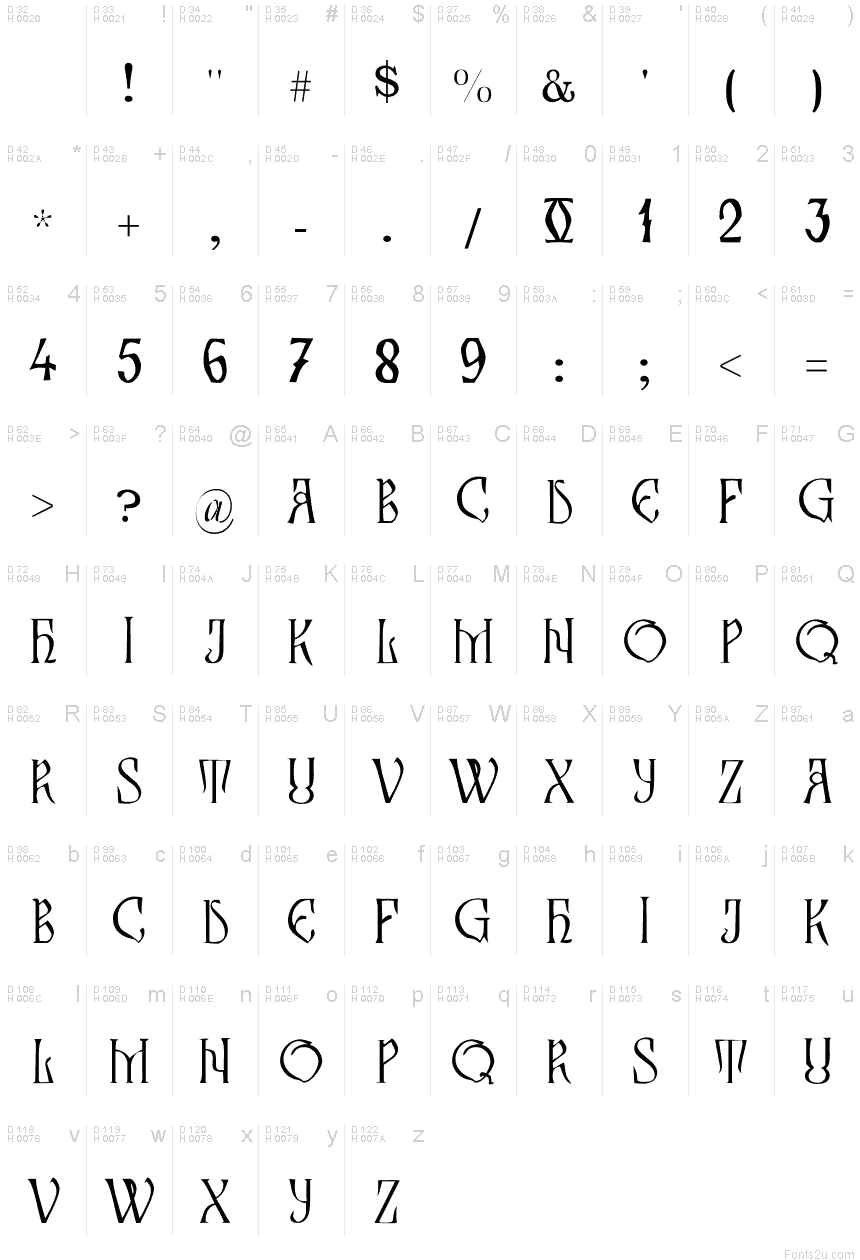
Zamolxis III to darmowy gotycki font typu display o smukłym, kaligraficznym rytmie i wyrazistym, średniowiecznym charakterze. Litery łączą ostre, klinowe pociągnięcia z zaokrąglonymi, niemal uncjalnymi krzywiznami, dzięki czemu krój sprawia wrażenie zarówno uroczystego, jak i nieco dziwnego – szczególnie widać to w szerokich łukach i zwężanych łączeniach.
Świetnie sprawdza się na okładkach książek fantasy, plakatach muzyki folkowej, w tytułach gier, brandingu o rytualnej tematyce oraz krótkich nagłówkach redakcyjnych, w których liczy się ten klimat „dawnego świata”. Jako darmowy font, Zamolxis III idealnie nadaje się również do monogramów, otwarć rozdziałów i szkiców logo, ponieważ litery mają wystarczająco dużo charakteru, by dobrze wyglądać nawet w krótkich tekstach.